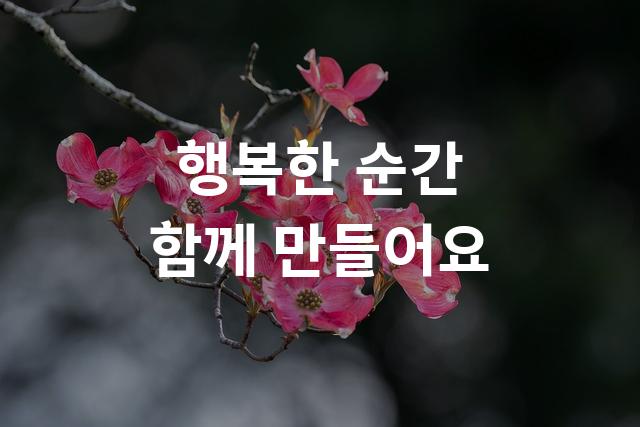
해피니스 산스는 현대백화점에서 제작한 기본 고딕 스타일의 폰트로, 문서 작성에 최적화되어 있으며 깔끔하고 명확한 느낌을 제공합니다. 간결한 디자인으로 어떤 내용도 세련되게 전달할 수 있습니다.
해피니스 산스은(는)
기본 고딕, 감성적인, 부드러움 계열의 생김새를 가지고 있으며
어린이 책, 인사말 카드, 소셜 미디어 등에서 자주 활용되며, 효과적인 메시지 전달에 적합합니다.
이 폰트는 라이프스타일, 이벤트/웨딩, 유아/가족 분야에 잘 어울리며,
친근한, 귀여운, 편안한 느낌을 담고 있는 것이 특징입니다.